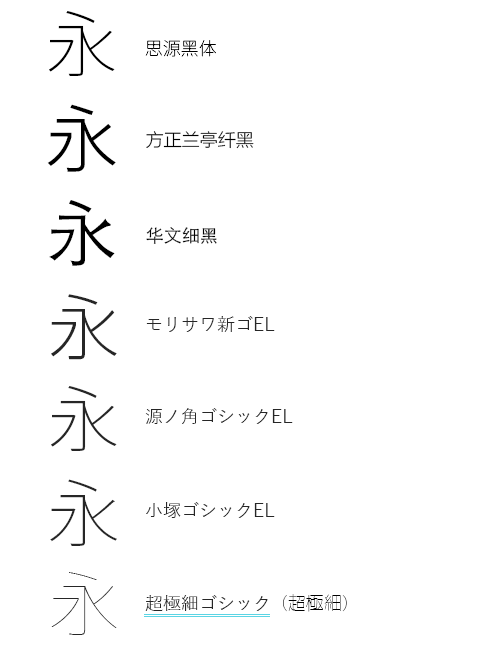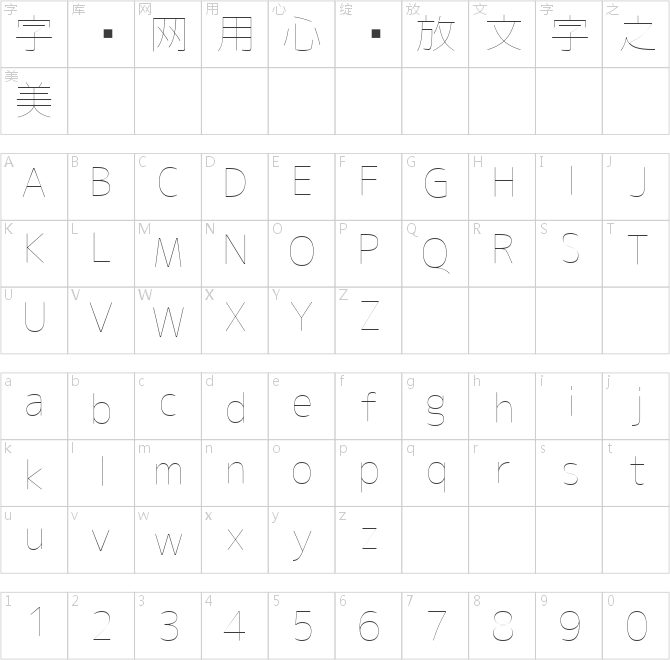
超極細字體
超極細字體介绍
超极细字体(日文名:超極細ゴシック体)是在M+字体的基础上进行细化加工的,以超极细为目标的一款字体。就像用圆珠笔和尺子描画的一样。是一款无杂质,有清洁感、透明感的时髦、清爽的字体。超极细超极细字体本身是日文字体,但同时支持繁体,所以也可作繁体字体使用。
使用该字体时的注意事项
因为非常细,所以在小文字使用或者在印刷的时候可能会变得模糊不清而看不见,请原谅使用范围有限。
挑战业界最细的字体
超极细,特色就是字体的线条十分细小,看起来像1PX精细,下面来一张字体对比图。可以看出超极细体在线条粗细方面完胜其它中文字体了,而且字体看起来也清晰,不会模糊,喜欢的可以下载使用,是免费的哦!